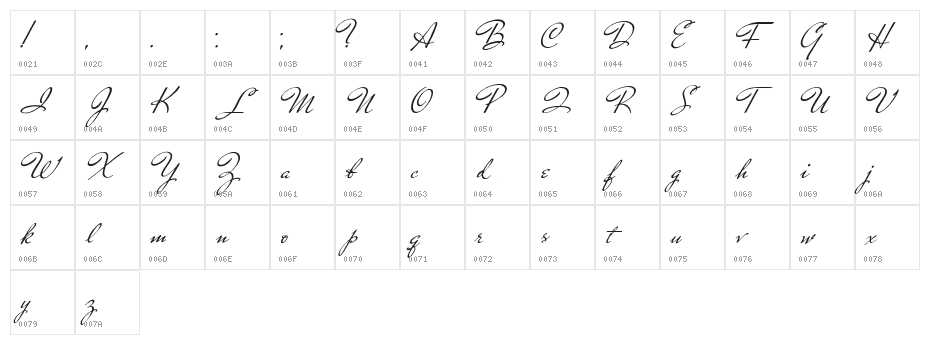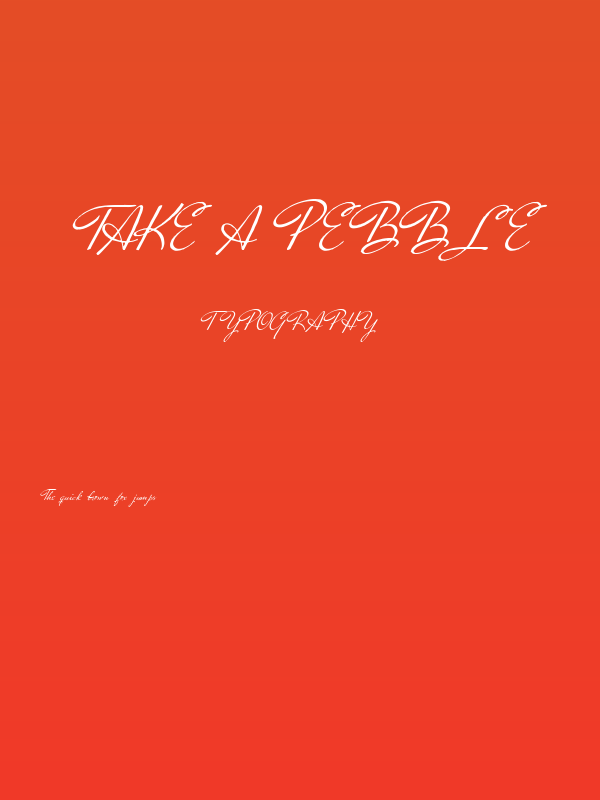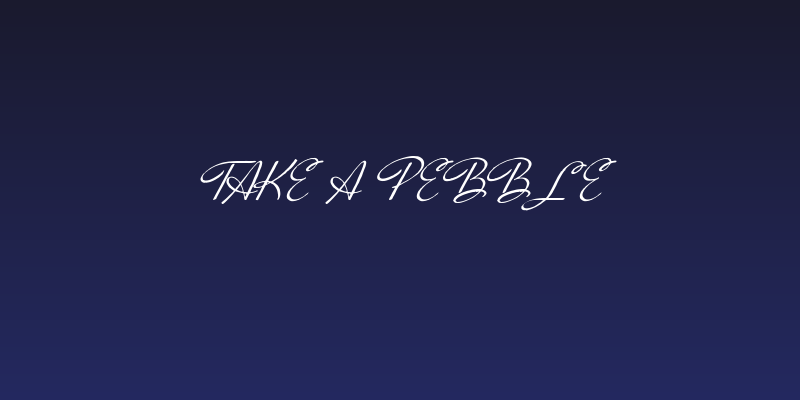
Take a Pebble Font
| Gesamtstil | Classic |
| Anwendungsfall | Logos, Invitations, Personal Correspondence |
| Vorgeschlagene Projekte | Ideal for wedding invitations, greeting cards, elegant branding, and personal stationery. |